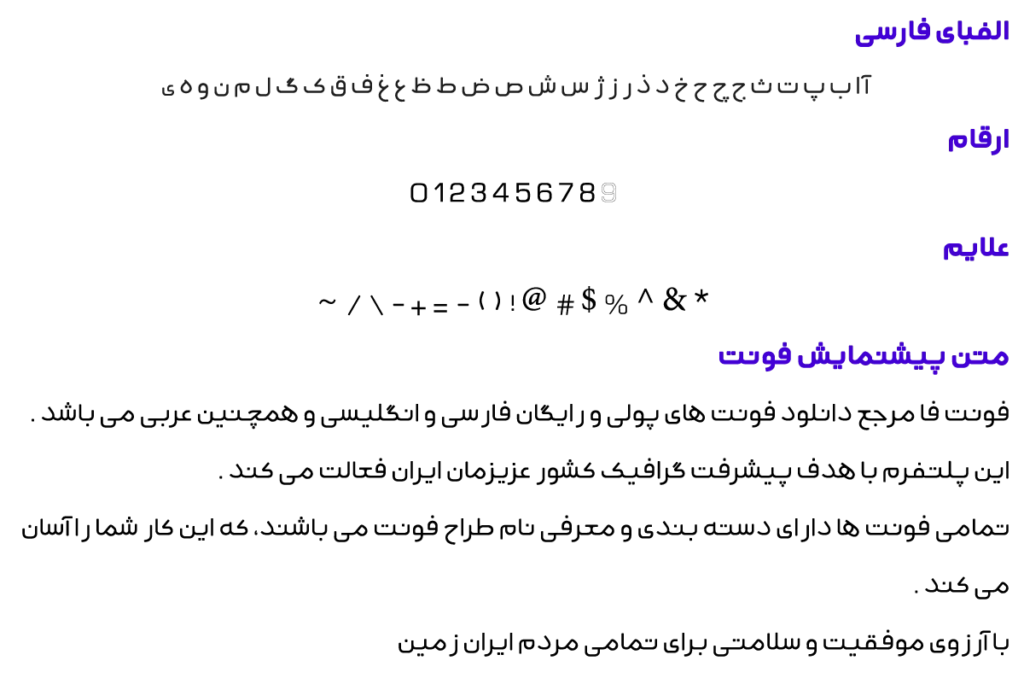
پیشنمایش فونت فناوری
فونت فارسی فناوری - Fanavari
توضیحات و معرفی فونت فناوری
فونت فارسی فناوری ( Fanavari ) از مجموعه فونت های آزاد و برتر می باشد، همچنان نوع فونت عنوان و متن و هندسی می باشد.
فونت شگفت انگیز و زیبای فوق توسط مرحوم استاد مسعود سپهر در سال 1399 طراحی و ساخته شده است.
همچنان فونت فناوری در 2 وزن پر رنگ و معمولی است.
• Fanavari Bold
• Fanavari Regular
تاپ فیس فناوری چگونه ایجاد شده است؟
همانطور که گفتیم این قلم زیبا توسط استاد گرامی برای وزارت ارتباطات و فناوری اطلاعات ساخته شده است.
طراحی این قلم بخشی از پروژه طراحی و اجرای هویت بصری این وزارت و یکی از مکعب های پازل هویت بصری است.
که در نهایت این تایپ فیس به پیشنهاد آقای آذری جهرمی وزیر ارتباطات و فناوری اطلاعات دولت دوازدهم نام گذاری شد.